Canvaでおしゃれな英字フォントを使って、SNSやブログのデザインをもっと魅力的にしたい!
でも、フォントが多すぎて「どれを選べばいいの?」と迷ってしまいますよね。
とはいえ、英字フォントは種類が多く、適当に選ぶと「イメージと違う…」なんてことも。
そこで今回は、Canvaで使える無料の手書き風英字フォント7選を厳選!
フォントの特徴やおすすめの使い方、おしゃれなデザイン例も紹介します。
- Canvaで無料で使える手書き風英字フォント7選
- フォント選びのコツとデザインのポイント
- ブログやSNSの発信力をアップする活用術
Canvaで無料で使えるおしゃれな手書き風英字フォント7選
Canvaには多くのフォントがそろっていますが、手書き風の英字フォントは特に人気があります。
ナチュラルな雰囲気や、エレガントな印象を簡単に演出できるのが魅力ですよね。
でも、種類が多すぎて「どれを選べばいいの?」と迷ってしまうことも。
そこで今回は、特におすすめの無料で使えるおしゃれな手書き風英字フォント7選を厳選しました!
ブログやSNSのアイキャッチ、資料作成など、さまざまな用途に活用できます。
まずは、どんなフォントがあるのか見てみましょう!
- Brittany(スタイリッシュ&おしゃれ)
- Parisienne(クラシック&ヴィンテージ)
- Alex Brush(エレガント&上品)
- Halimum(流れるような筆記体)
- Daydream(太めでかわいい雰囲気)
- Angella White(細身で女性らしい)
- MoonTime(シンプル&ナチュラル)
1. Brittany(スタイリッシュ&おしゃれ)
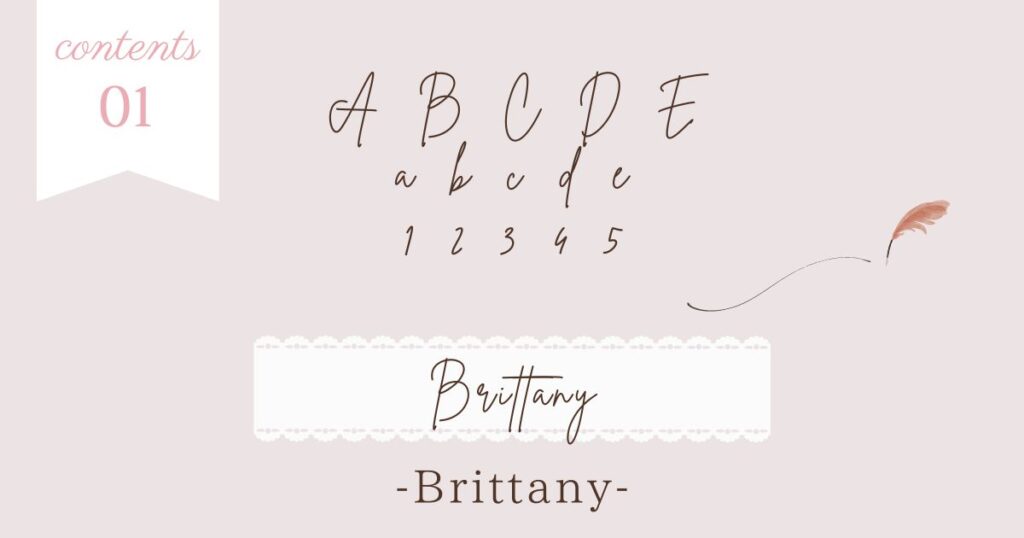
「Brittany」は、スタイリッシュでモダンな雰囲気の手書き風英字フォント。
洗練されたデザインにぴったりです。
特に、大文字がやや大きくなる特徴があるため、タイトルやキャッチコピーに使うと目を引くデザインに仕上がります。
2. Parisienne(クラシック&ヴィンテージ)
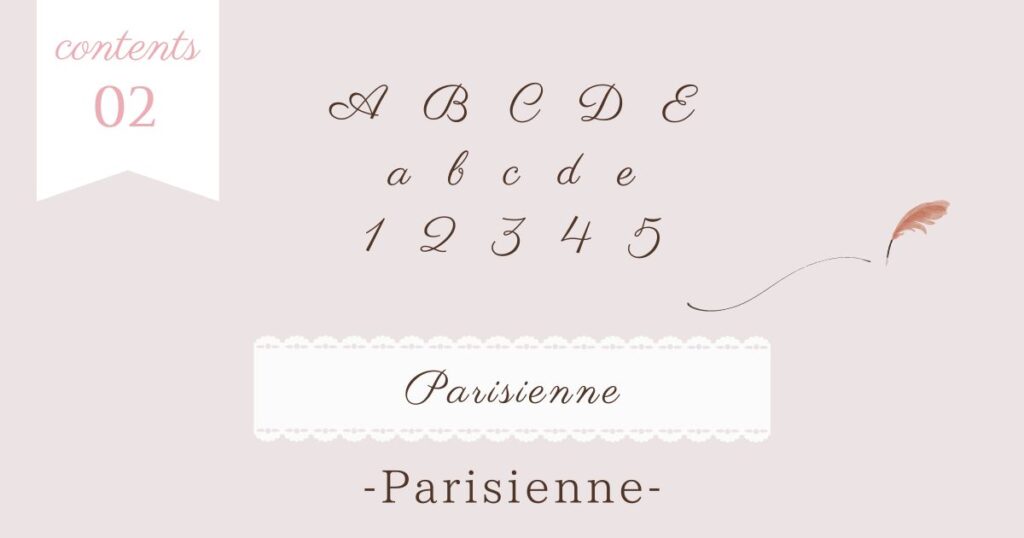
「Parisienne」は、パリを感じさせるクラシックでヴィンテージな筆記体フォント。
少し不揃いな筆のタッチが特徴で、ナチュラルな雰囲気を演出できます。
エレガントなデザインや、温かみのあるロゴ作成にもおすすめです。
3. Alex Brush(エレガント&上品)
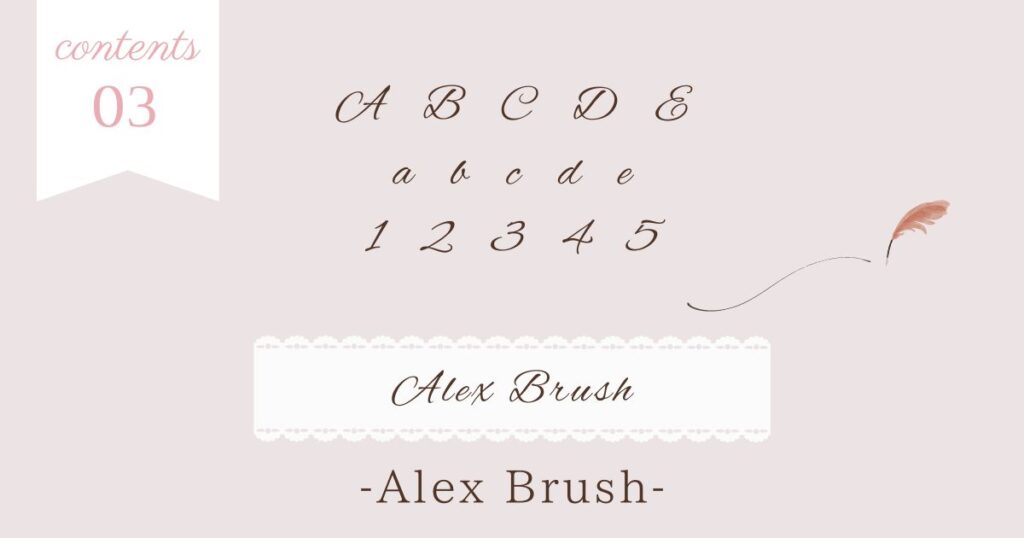
「Alex Brush」は、繊細でエレガントな筆記体フォント。
ウェディングカードや、高級感のあるデザインに最適です。
特に大文字が美しく装飾されているため、タイトル部分に使うとより映えます。
4. Halimum(流れるような筆記体)
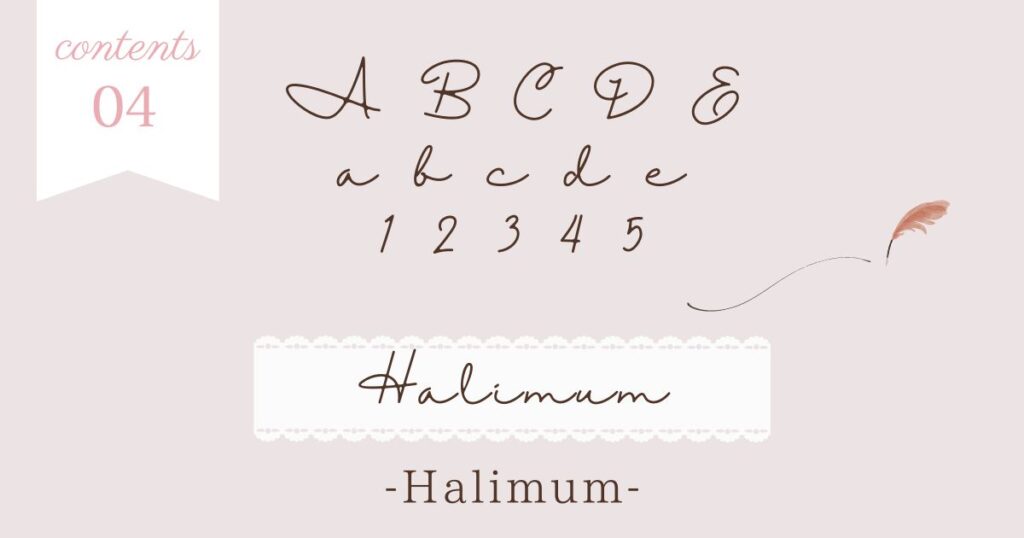
「Halimum」は、流れるような筆記体が特徴の手書き風フォント。
柔らかくて品のある文字デザインが魅力です。
洗練された印象があるため、ロゴデザインやブランド名の表記などにもおすすめ。
特に、シンプルな背景と合わせるとより美しく見えます。
5. Daydream(太めでかわいい雰囲気)
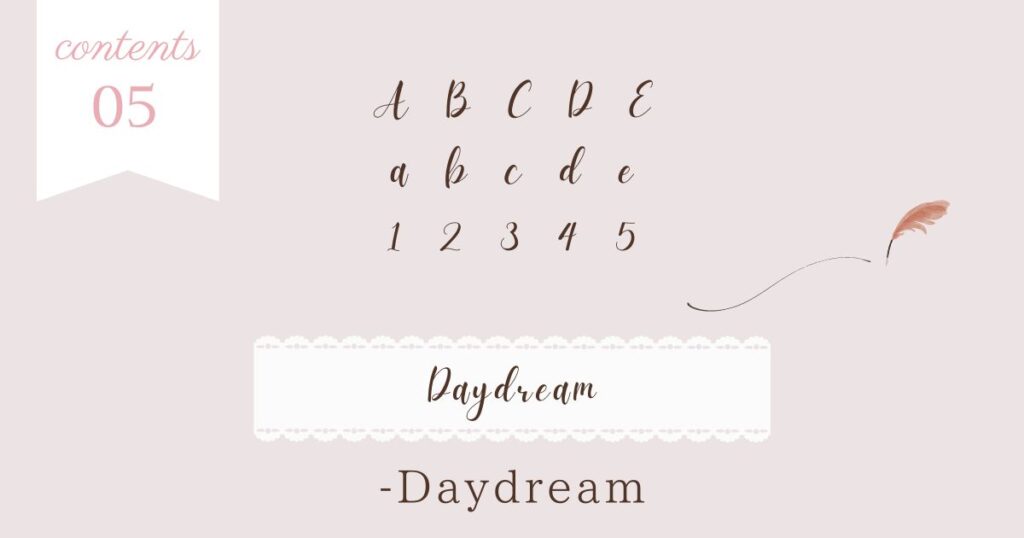
「Daydream」は、やや太めの文字が特徴で、ポップでかわいい雰囲気を演出できるフォントです。
SNSの投稿画像やYouTubeのサムネイル、アイキャッチなどに最適!
程よい太さがあるため、視認性も抜群です。
6. Angella White(細身で女性らしい)
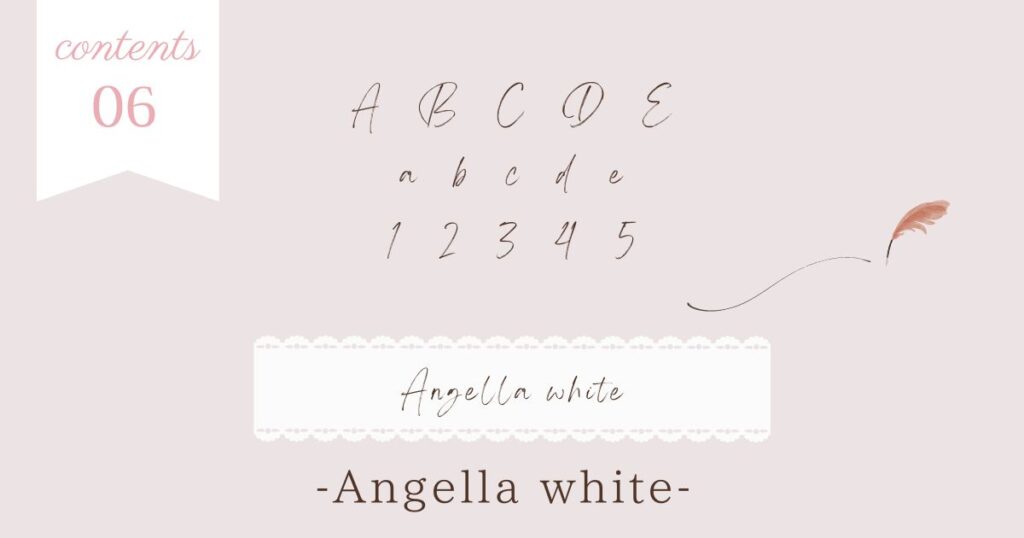
「Angella White」は、細身で繊細な筆記体フォント。
女性らしく優雅な雰囲気を持っています。
フェミニンなデザインや、高級感を演出したいときにぴったり。
ジュエリーやアパレルブランドのロゴなどにもよく使われます。
7. MoonTime(シンプル&ナチュラル)
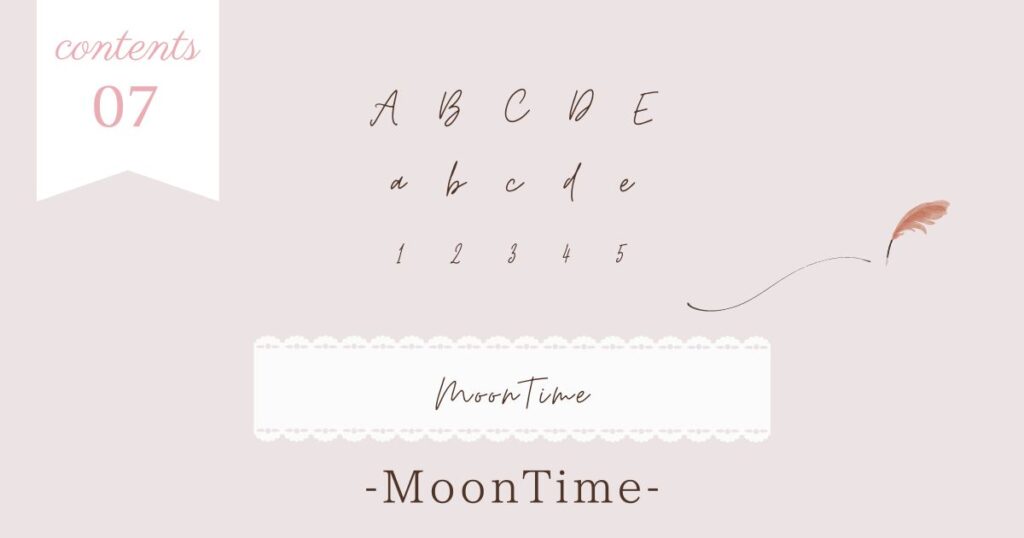
「MoonTime」は、シンプルでナチュラルな雰囲気が魅力の筆記体フォント。
クセが少なく、どんなデザインにも馴染みやすいのが特徴です。
シンプルなロゴや、ミニマルなデザインにぴったり。
汎用性が高いため、幅広い用途で活用できますよ。
手書き風フォントを活用すれば、シンプルなデザインもグッとおしゃれになりますね♪
手書き風英字フォントを使ったCanvaデザイン例
Canvaで手書き風の英字フォントを使うと、デザインに温かみや個性をプラスできます。
でも、どのフォントがどんなデザインに合うのか、迷うこともありますよね。
そこで今回は、Canvaを使って実際にデザインを作成し、それぞれのフォントの雰囲気が伝わるようにしました。
おしゃれなフォントを活かしたデザイン例を見ながら、あなたのブログやSNS投稿、資料作りの参考にしてみてくださいね。
例1. Parisienneを使ったサンクスページ
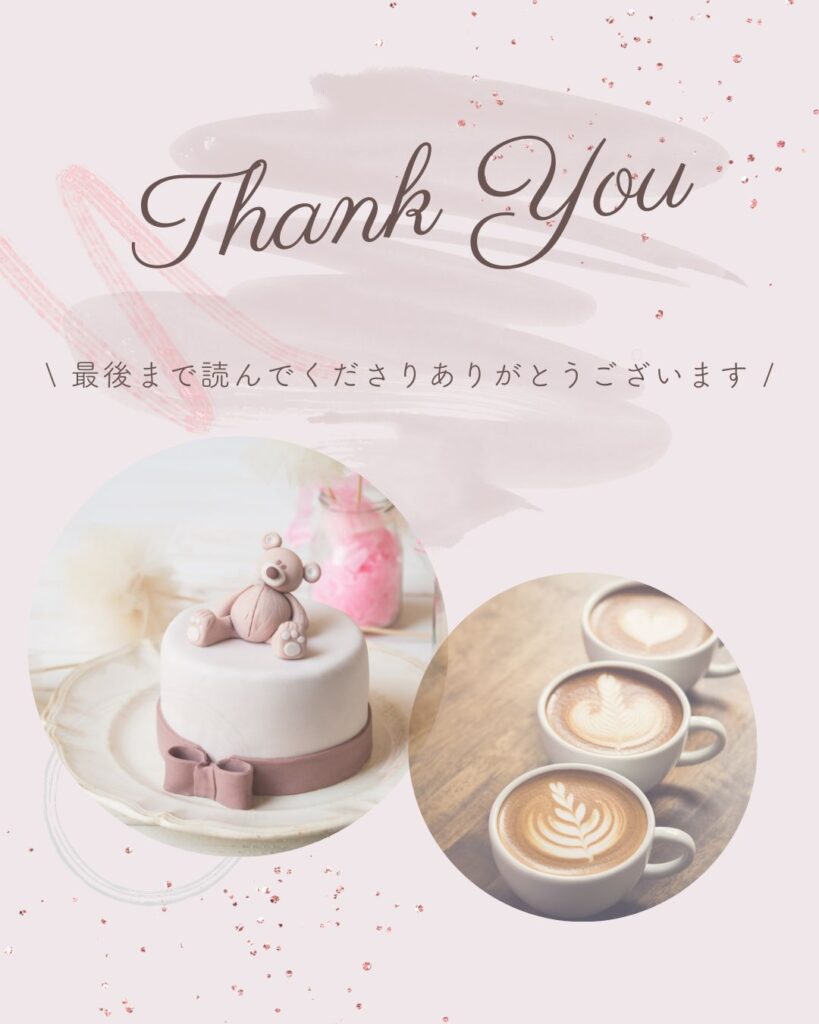
Parisienne(パリジェンヌ)は、クラシックな雰囲気とかわいらしさを兼ね備えた手書き風の英字フォントです。
流れるような筆記体が特徴で、エレガントな印象を与えてくれます。
今回は、シンプルなサンクスページのデザインに使用してみました。
柔らかい雰囲気が出るので、おしゃれで洗練された印象になりますね。
パステルカラーやシンプルな背景と組み合わせると、より美しくまとまります。
「Parisienne」を使うと、シンプルなデザインでもグッと上品な雰囲気に仕上がりますよ♪
例2. Alex Brushを使ったウェディングカード
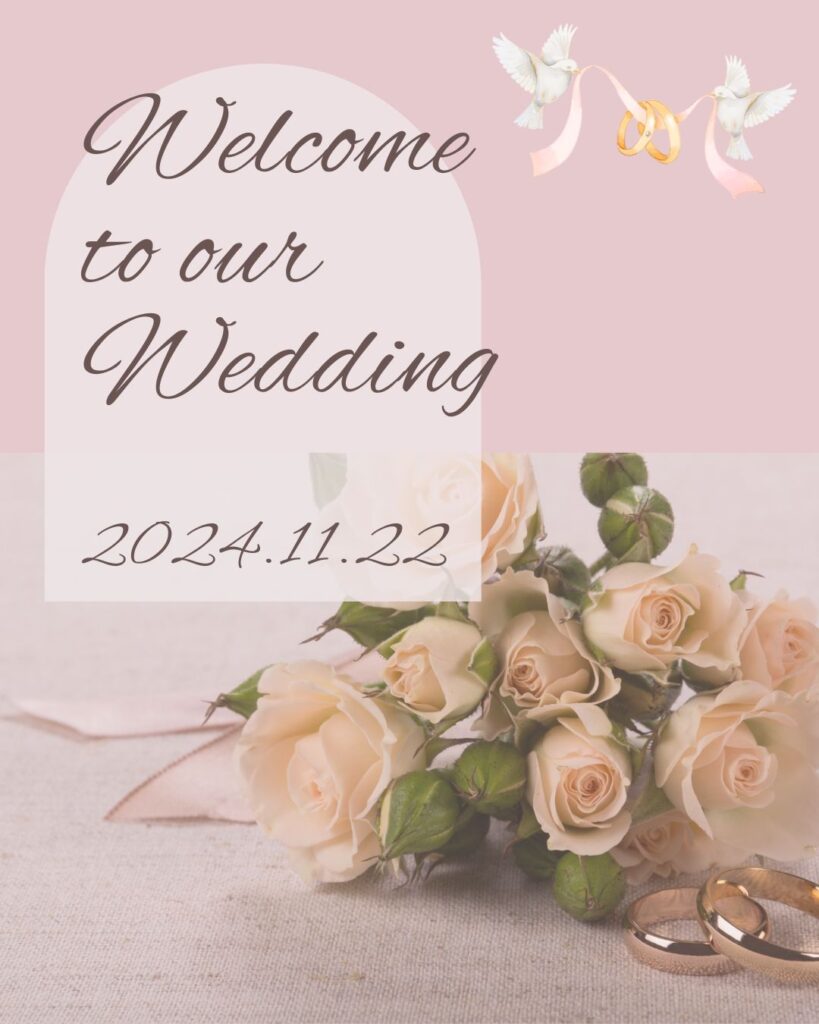
Alex Brushは、エレガントで洗練された筆記体フォント。
特に、大文字が美しく装飾されているため、特別なシーンのデザインにぴったりです。
今回は、ウェディングカードのデザインに使用してみました。
フォーマルな雰囲気が出るので、結婚式の招待状や感謝状、ブランドのロゴデザインにも活用できます。
シックな背景と組み合わせると、より高級感のある仕上がりになりますよ。
「Alex Brush」は、特別なシーンにぴったりな大人かわいいフォントですね♪
まとめ|手書き風英字フォントで副業のデザインを格上げ!
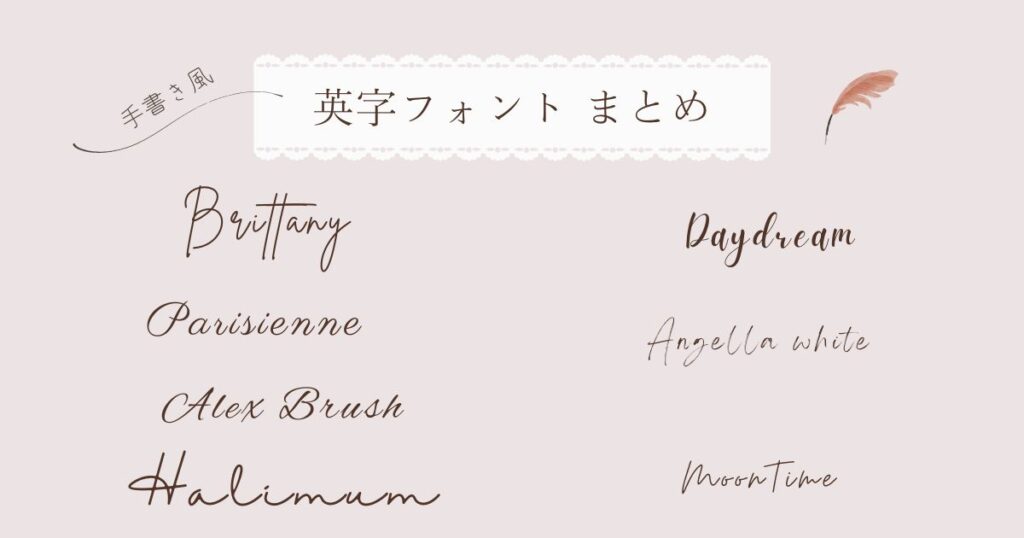
今回は、Canvaで無料で使える、おしゃれな手書き風英字フォント7選を紹介しました!
- おしゃれでかわいい英字フォント7種類を厳選
- デザイン初心者でも使いやすいフォント選びのコツ
- 副業ブログやSNSのデザインをワンランクアップ
手書き風英字フォントは、シンプルなデザインに個性とおしゃれさをプラスできます。
無料で使えるCanvaのフォントを活用して、魅力的な投稿やアイキャッチを作りましょう!
おしゃれなフォントを使うと、デザインの印象がガラッと変わりますね!